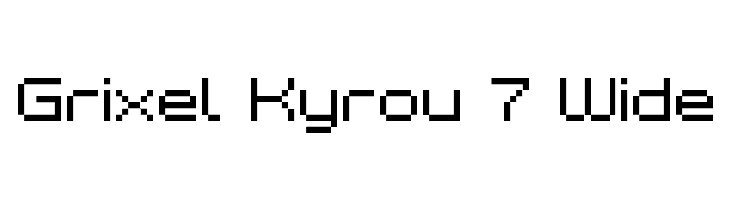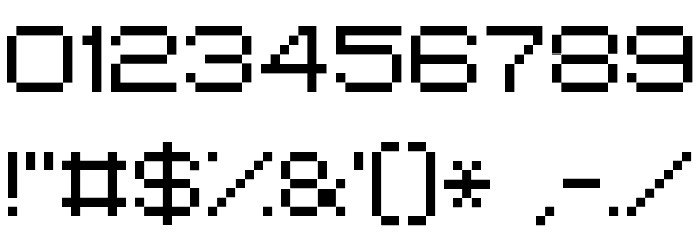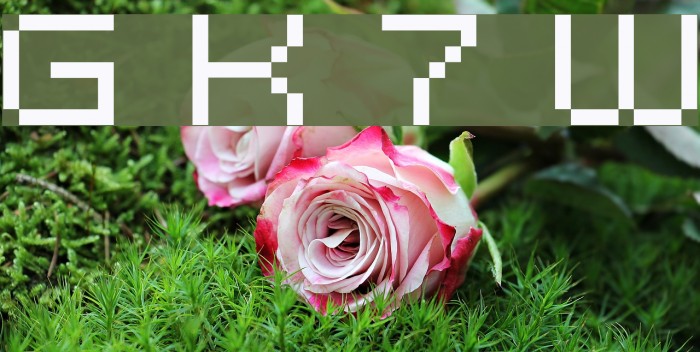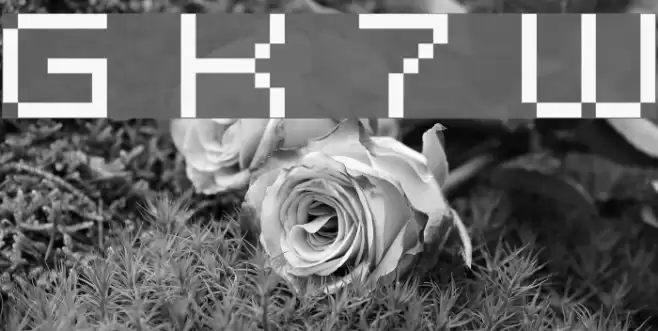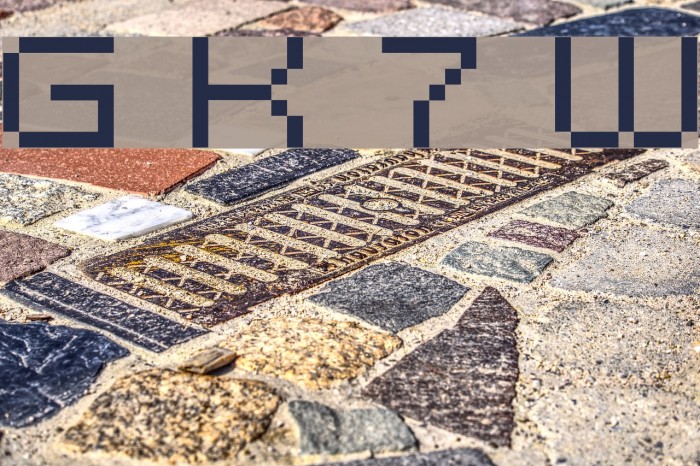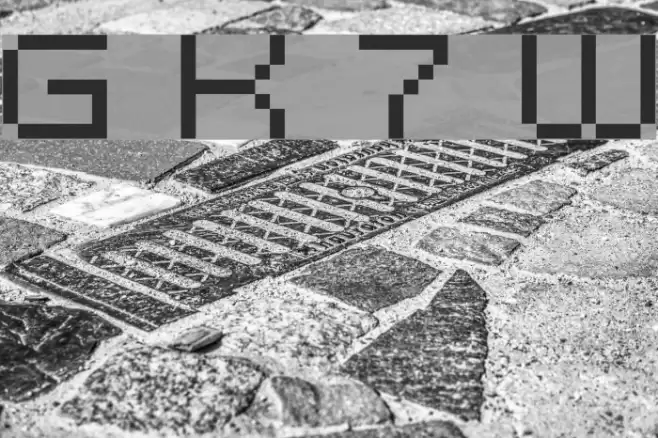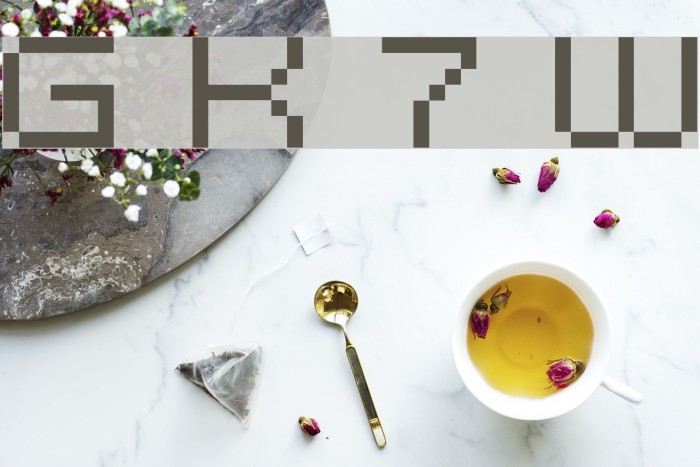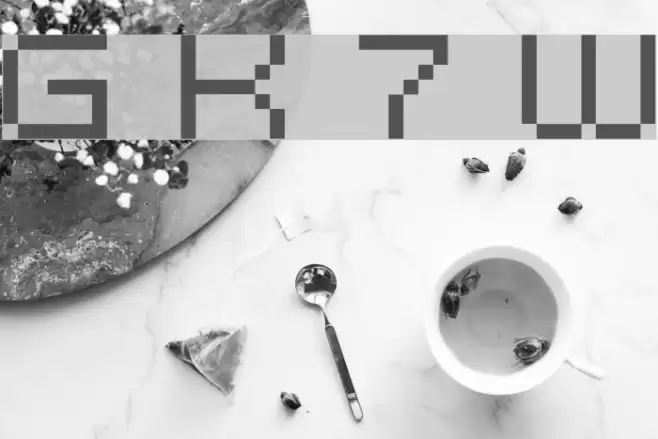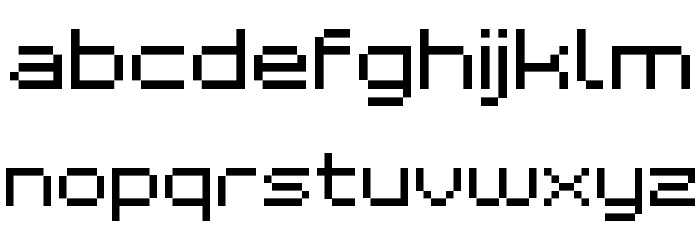
Grixel Kyrou 7 Wide Font
✎ Pixel
| 名前 | Grixel Kyrou 7 Wide |
| カテゴリ | Pixel |
| 用途 | Headlines, Logos, Digital Art |
| おすすめプロジェクト | Ideal for retro video games, digital art projects, tech-themed posters, and any design that seeks to capture a vintage digital aesthetic. |